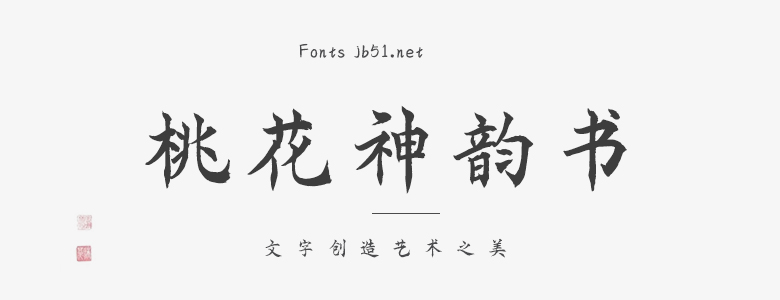
桃花神韻書(shū)是一款獨(dú)特且富有藝術(shù)性的字體,它的設(shè)計(jì)靈感源于中國(guó)傳統(tǒng)的書(shū)法藝術(shù)和桃花的美麗。這款字體將傳統(tǒng)書(shū)法的韻味與現(xiàn)代字體設(shè)計(jì)理念相結(jié)合,形成了一種非常具有個(gè)性和魅力的風(fēng)格。 桃花神韻書(shū)的字母結(jié)構(gòu)嚴(yán)謹(jǐn)而富有變化,筆畫(huà)粗細(xì)得當(dāng),線條流暢自然。在保持文字可讀性的同時(shí),每個(gè)字母都經(jīng)過(guò)精心設(shè)計(jì),呈現(xiàn)出獨(dú)特的曲線美和節(jié)奏感。字體的曲線部分流暢優(yōu)雅,像是流動(dòng)的泉水,給人一種柔和舒適的感覺(jué)。 這款字體的特點(diǎn)在于其獨(dú)特的桃花圖案裝飾。在字母的起筆、收筆以及一些關(guān)鍵的筆畫(huà)位置,設(shè)計(jì)師巧妙地融入了桃花的圖案元素,使得整個(gè)字體看起來(lái)既傳統(tǒng)又現(xiàn)代,充滿了藝術(shù)感和文化內(nèi)涵。這些桃花圖案不僅增加了字體的美觀性,也使其更具識(shí)別度。 桃花神韻書(shū)非常適合用于具有文化內(nèi)涵或藝術(shù)性的文本。它可以用于書(shū)籍、報(bào)紙、雜志等印刷品,也可以用于廣告、海報(bào)、包裝等平面設(shè)計(jì)。同時(shí),由于其獨(dú)特的書(shū)法韻味和桃花圖案,桃花神韻書(shū)也非常適合用于中國(guó)的傳統(tǒng)文化、藝術(shù)和旅游等相關(guān)領(lǐng)域的宣傳。 總的來(lái)說(shuō),桃花神韻書(shū)是一款充滿個(gè)性和魅力的字體,它將傳統(tǒng)與現(xiàn)代完美結(jié)合,給人留下深刻的印象。無(wú)論是在印刷品還是平面設(shè)計(jì)中,桃花神韻書(shū)都將為文本增添獨(dú)特的藝術(shù)魅力和文化內(nèi)涵。